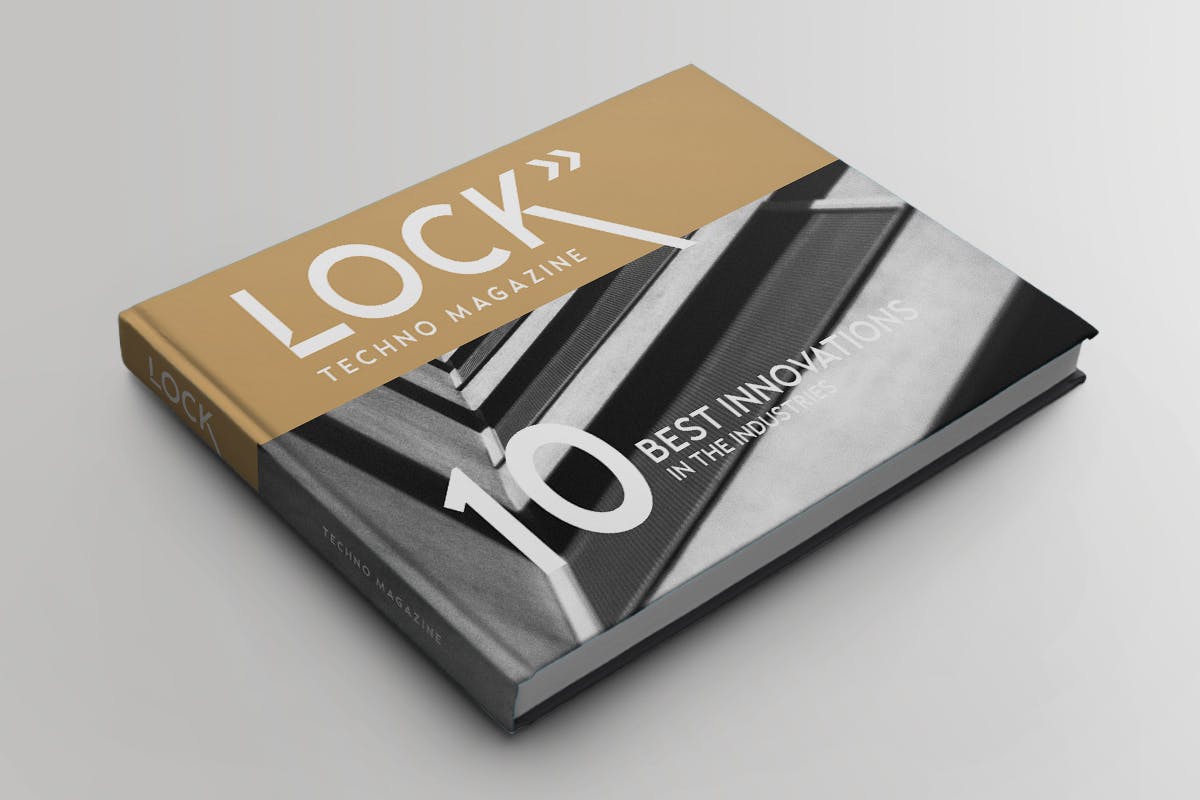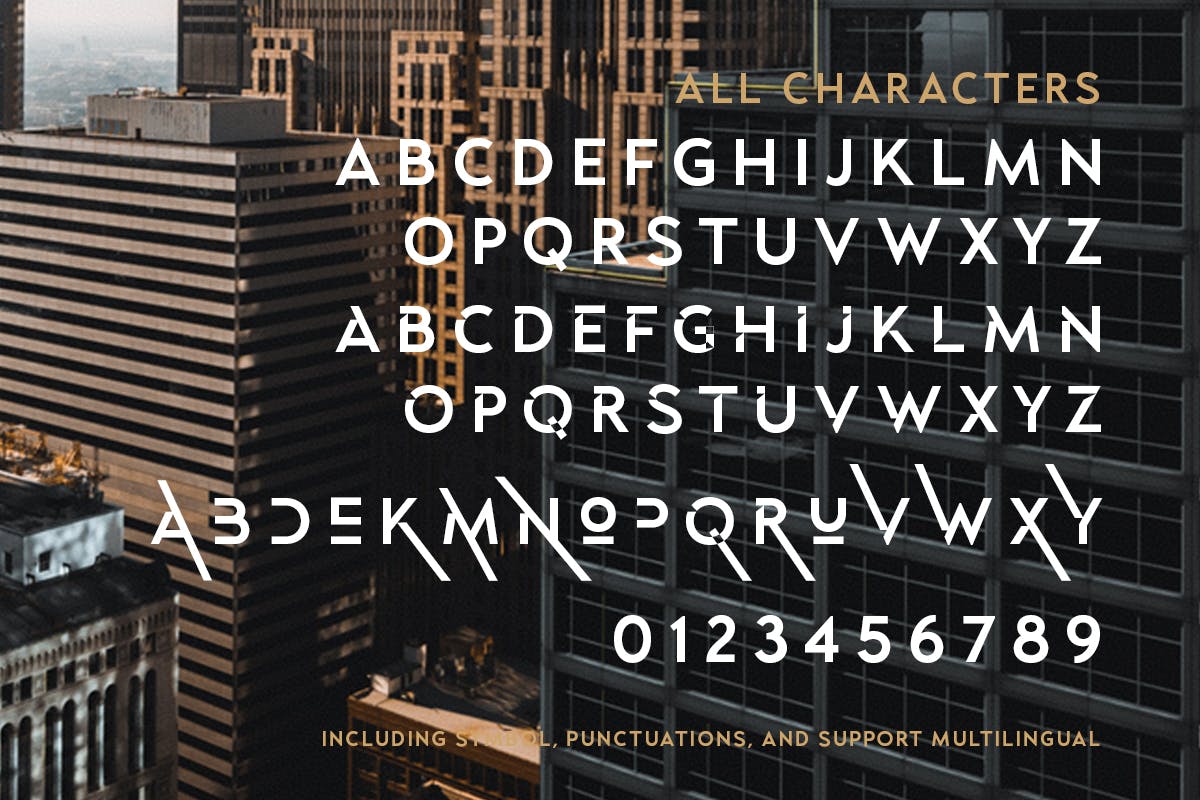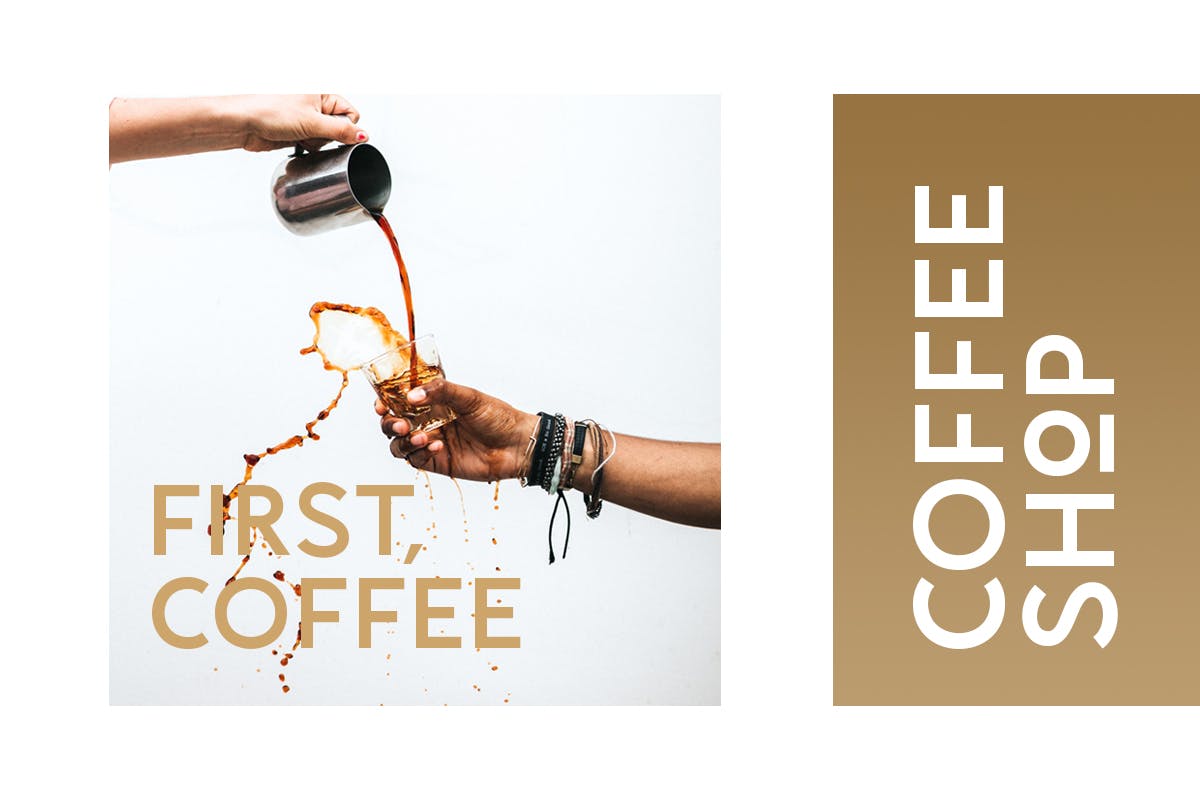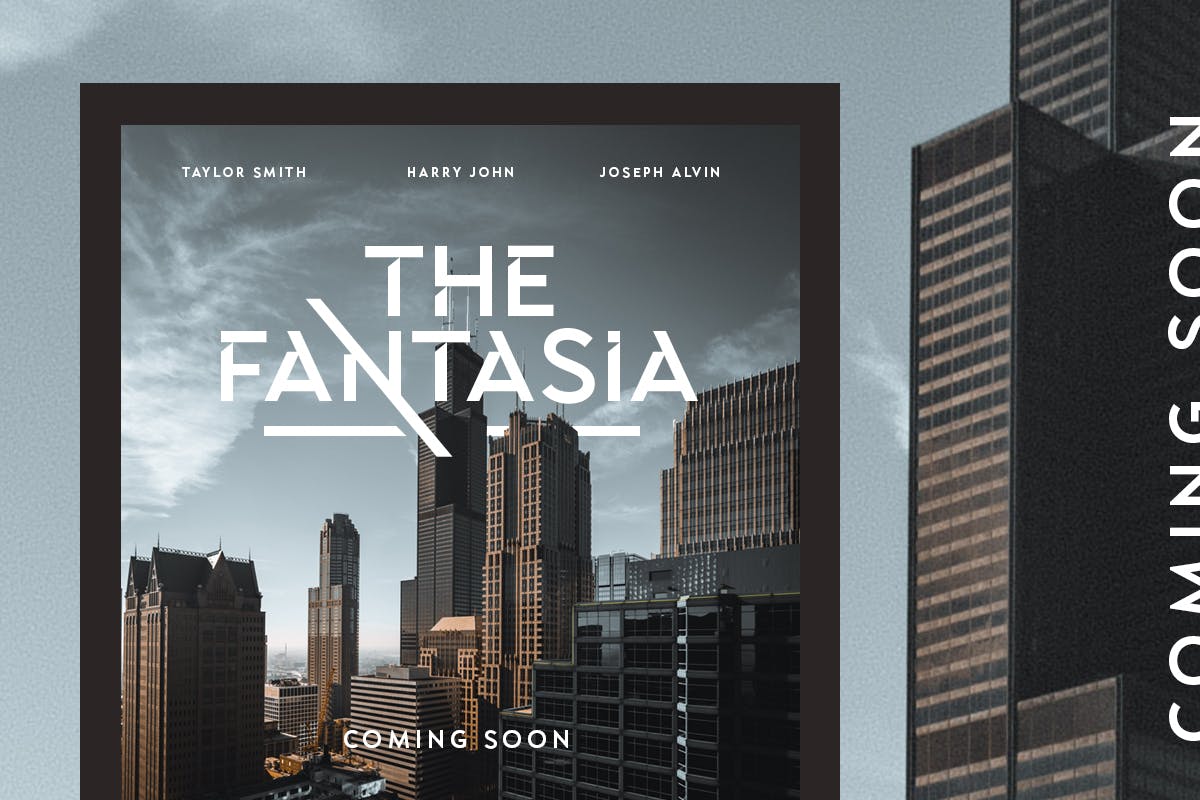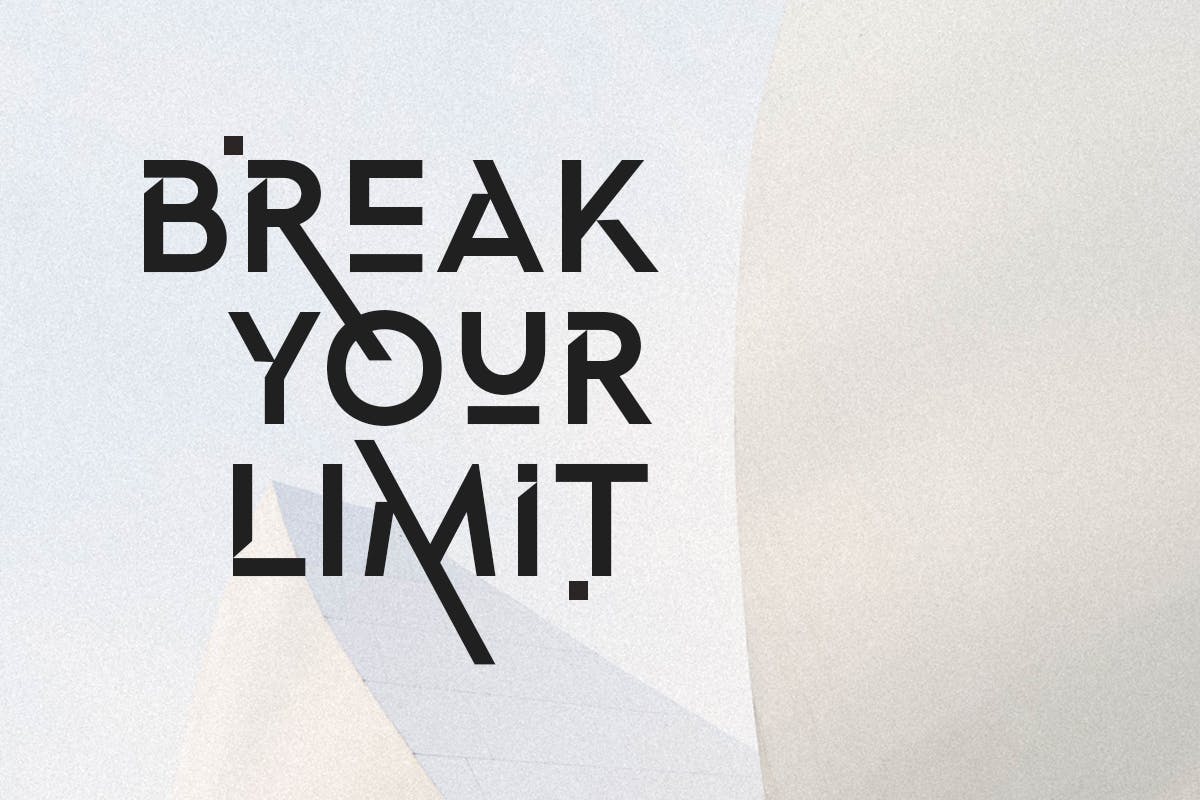
معرفی فونت Blackpast، یک فونت لوگو آیندهنگر با جایگزینهای منحصر به فرد!
Blackpast یک فونت بدون سریف است که دارای حروف کوچک خاصی است که طراحی شما را به شکلی مدرن و آیندهنگر نشان میدهد. شما میتوانید از این فونت برای هر نوع طراحی، به ویژه برای ساخت لوگوتایپ استفاده کنید. با ترکیب حروف بزرگ و کوچک، میتوانید لوگوی خود را خواناتر کنید. این فونت همچنین دارای جایگزینهای ویژهای است که طراحی شما را متمایزتر خواهد کرد!